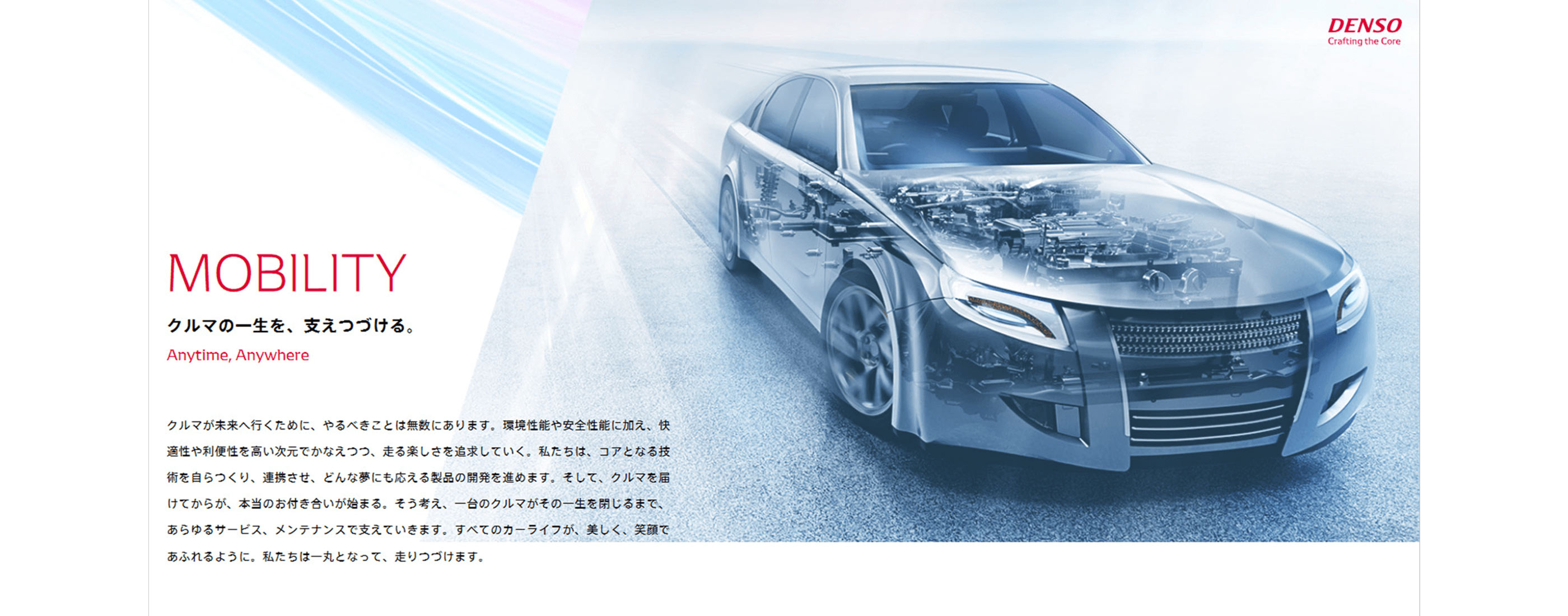
デンソー フィットフォントプロジェクト
コントラプンクトとの協業
未来は語るものではなく、つくるもの。デンソーはこれまでも、画期的な製品や機器のための革新的な技術を提供してきました。「100 年に一度」と言われる自動車業界の変化の中で、世界を見据えた新たな未来をつくるために、「人にとって大切なものを創り上げ、磨き続ける」という思いをこめた「Crafting the Core」というコーポレートスローガンを制定しました。最初に着手したのは、伝統や品質、世の中に向けてデンソーが大切にしていることを伝えたいという、熱い思いが込められた DENSO ロゴの進化と、それを基盤として展開するコーポレートフォントの開発でした。
「SNS を使った展開など、自社で開発することができるメディアが重要性を増していく中で、フォントの存在がよりクローズアップされています。欧米の企業では、広告やプロダクトラインなどで一貫したイメージを発信するために、コーポレートフォントを使うことが多く見受けられます。より広くコミュニケーションをするために、そして印象を残すための大事なツールとして、フォントが必要だという機運が高まりました。世界を見据えた展開のために、最初に取り組んだのがオリジナル欧文書体の開発です。そこでパートナーに選んだのがKontrapunkt (コントラプンクト) でした。実績はもちろん、欧州を拠点にしていること、そしてデザインに対する姿勢に共感できていたので、最良のパートナーだと思いました」と、株式会社デンソー 広報部 ブランド推進室 宣伝制作課 課長・村松 正巳氏は語ります。
コントラプンクトは、デンマークのコペンハーゲンに本拠地を置き、戦略的デザインとブランディングの分野において、北欧をリードするブランディングエージェンシーです。コーポレートフォント開発は、20年前から使用しているDENSO ロゴを変えずに進化、洗練させること、ロゴに込めた思いを反映することが条件でした。最初に、1996 年から使用しているDENSO ロゴの文字のバランスやアンカーポイントの整理、カラー設定などを相談するところから始めたといいます。欧文コーポレートフォントの開発は、DENSO ロゴの狙いを書体に反映するため、一定のレンジの中から突き詰めて行くというプロセスをとりました。以前は、既存のHelvetica というサンセリフ書体を制定フォントとして使用していましたが、DENSOロゴとの親和性を高めるため、セリフ書体体を先行して開発し、続けてサンセリフ体も整備しました。グローバル展開を前提としているため、欧米やアジアの各拠点にも、それぞれの文化を背景とした視点からの意見を求めました。また、社内デザイナーから使用感などの意見を集めてコントラプンクトに伝え、フォントの精度をあげることに注力しました。
「欧文書体の完成が近づいたところで、日本語はどうしようかということになりました。和文書体の開発には時間もコストもかかることを知っていたので、オリジナルの開発には手を出せないと思っていました。そんな時にフィットフォントに巡り会ったのです。書体をセミオーダーできるサービスがあるとは思っていなかったので、光がさした感じでした。新ゴが制定書体となっていましたが、デザイン部では以前からAXIS Font をいろいろなコミュニケーションの場面で使用していたので、AXIS Font をベースにしたフィットフォントを導入することに、全く抵抗がありませんでした」
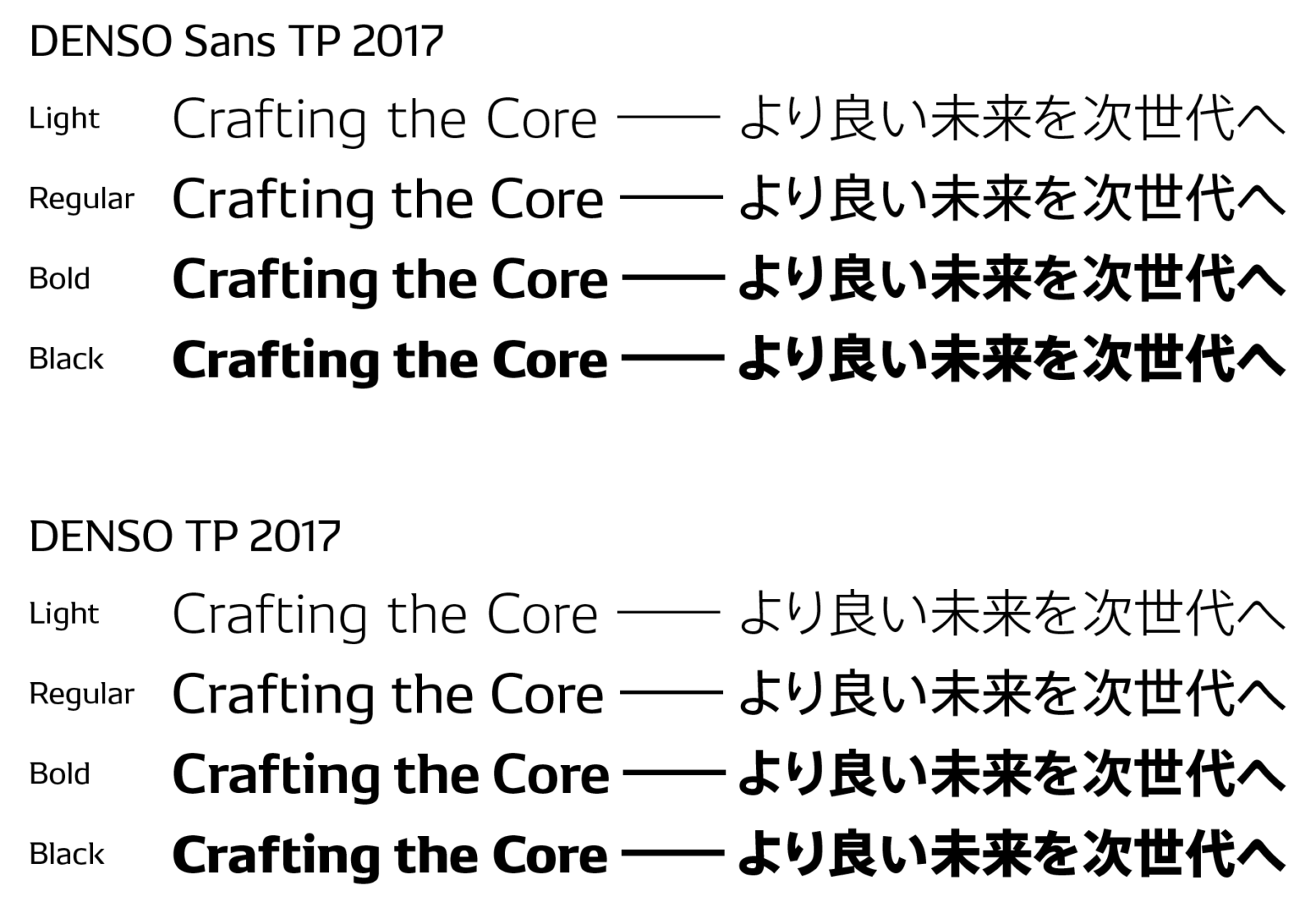
タイププロジェクトは、自社のフィットフォント技術により、コントラプンクトが開発した欧文フォントに合わせてAXIS Font のウエイトを調整し、「DENSO TP 2017」「DENSO Sans TP 2017」として提供しました。このデンソー初のコーポレートフォントは、2017 年1 月からWeb サイトやTV コマーシャル、交通広告、新聞広告で運用が開始され、会社案内や全社員の名刺、レターヘッドなどでも、すべて「DENSO TP 2017」が使用されています。コーポレートフォントが完成したことで、スムーズなプロジェクトの開始が実現できることに期待していると言います。
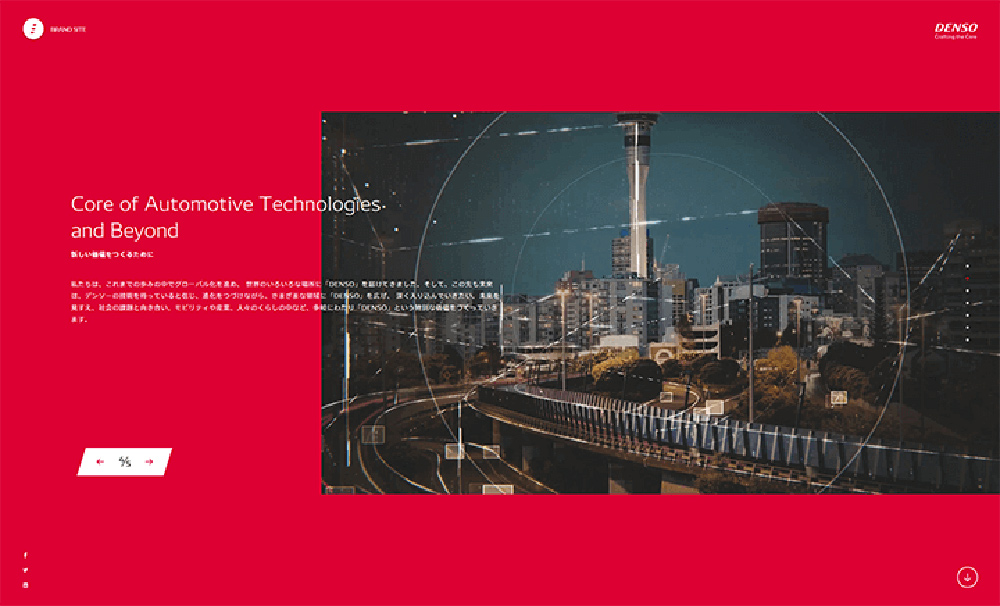
「クリエーションのスタートに、デンソーのアイデンティティが込められたコーポレートフォントが在るということに価値があります。お客様とのタッチポイントすべてで、同じデザインメッセージで届けることによって、蓄積されていくものがあると思います。デンソーは、B to B 企業なので、タッチポイントはあまり多くありませんが、メディアが効率的に連携してお客様のイメージの中に染み込んでいってくれたら、と思っています」
欧米では、文化として書体のリテラシーが進んでいます。今後、日本においても書体に対するリテラシーがより向上していく中で、デンソーはコーポレートフォントを通じて、ものづくりへのこだわりを発信し続けます。